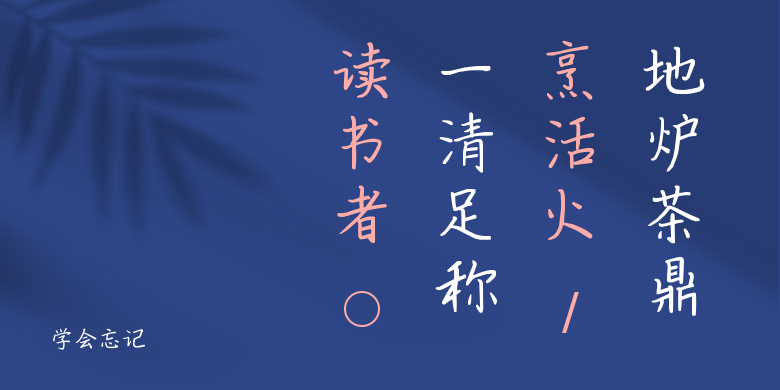
学会忘记
学会忘记,这款字体结构工整、笔画清晰,兼顾美观与易读性,适用于标题、正文、海报、包装、LOGO 等多种场景。字形优雅稳定,风格百搭耐看,适配日常排版与创意设计,让文字呈现更舒适、更具质感。学会忘记一笔一画,皆是细节,以均衡的比例、流畅的线条打造舒适视觉体验,字形端正大气,风格简约现代。无论是商业设计、品牌宣传还是日常排版,都能轻松驾驭,让文字更有格调与力量。学会忘记字体下载。